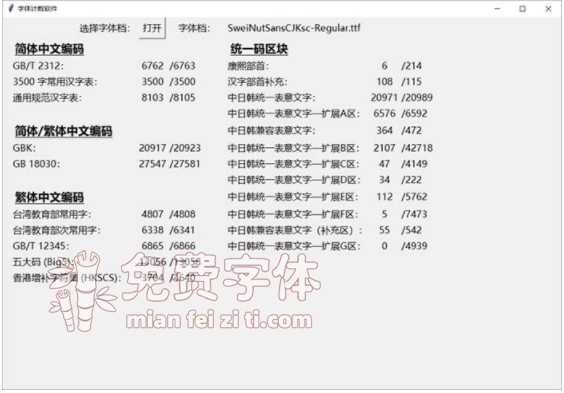
狮尾螺帽黑体:思源黑体增加斜角和拔脚改造免费商用字体字体资讯
狮尾螺帽黑体基于思源黑体增加斜角和拔脚改造,更加简明现代化的字体。支援简体中文、繁体中文、韩文与日文;欢迎大家自由应用、自由优化、自由改作!
狮尾螺帽黑体的特色是,“口”字的转角处增加一个斜角,外形有点像螺帽。
狮尾螺帽黑体和狮尾螺帽腿黑体差别在有没有拔脚,“拔脚”就是会有较少的笔画,例如移除“口”字的左右下角会多出的短线条。有拔脚的字会较圆,但是会造成有些字因直接去掉腿后左右不平衡、左右不对称的“悬空”问题。改使用“腿”系列字体就不会有这个问题。
下面这个图统计了这款字体里面包含多少个简体字数繁体字数等信息,方便大家直观地了解这款字体的简繁字体数量。